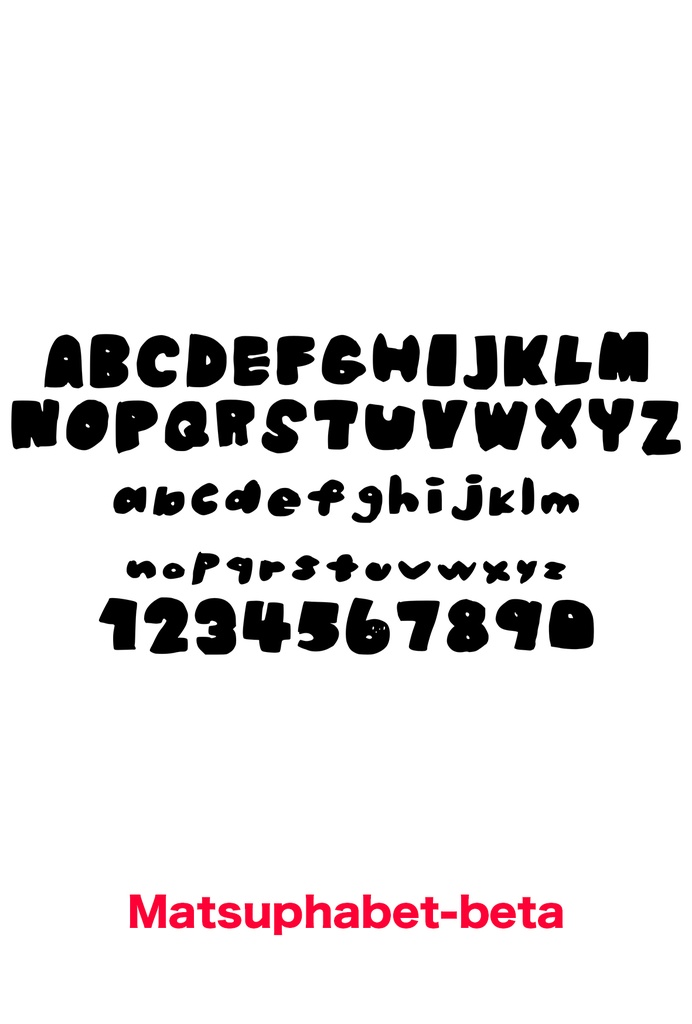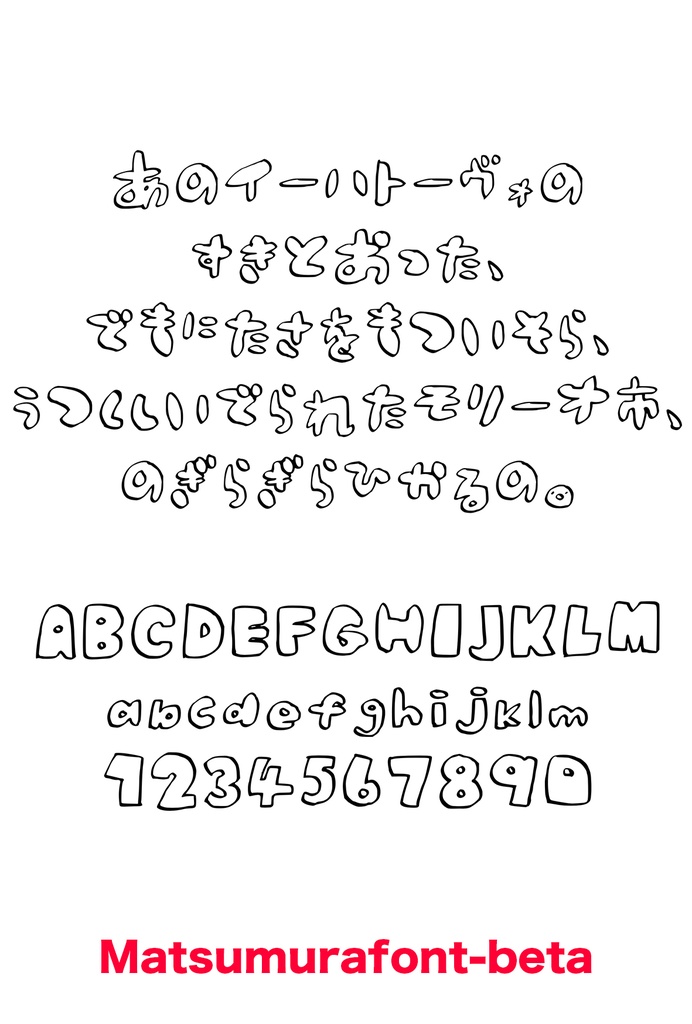
まつむらフォント【試作中】
松村が適当に作った試作のフォントです。 試作かつほぼほぼ自分用に作ったものなので使い勝手などは保証しません。 (macとwindowsで一応動作を確認しています) ・Matsuline-alpha.ttf ひらがなとアルファベット大文字&小文字と数字に対応。 ・Matsuphabet-beta.ttf 太めのアルファベット大文字&小文字と数字に対応。 ・Matsumurafont-beta.ttf ひらがなとごくわずかな常用漢字、アルファベット大文字&小文字と数字に対応。 ですが、無駄に白抜きで作ったので使い勝手は死ぬほど悪いです FontForgeあたりでちゃんとしたものをちょこちょこ作って2023年8月くらいまでにはアレしたい気持ちはあるので応援してくれるとうれちい ●ご購入者様は以下のファイルをダウンロード可能になります ・MatsuFontBeta.zip →Matsuline-alpha.ttf Matsuphabet-beta.ttf Matsumurafont-beta.ttf ●権利、使用可能範囲について ・個人的利用→OK ・フォントデザインを改変して使用→OK ・商用利用→OK(例:動画や漫画の中で使う、プレゼン資料やポスターデザインに使う、など) ・二次配布、二次販売、転売→NG ・自作発言→NG その他、常識の範囲内での使用はOKです (過激な思想や反社会的な内容を含む場合や、公序良俗に反する使用はご遠慮ください) Rights and Scope of Permitted Use Modification of the font design→OK Commercial use→OK (e.g., use in videos and cartoons, presentation materials, poster design, etc.) Secondary distribution, secondary sales, and resale→NG Self-created remarks→NG Other uses within the bounds of common sense are OK (Please refrain from using the materials if they contain radical ideas or antisocial content, or if they are offensive to public order and morals.)